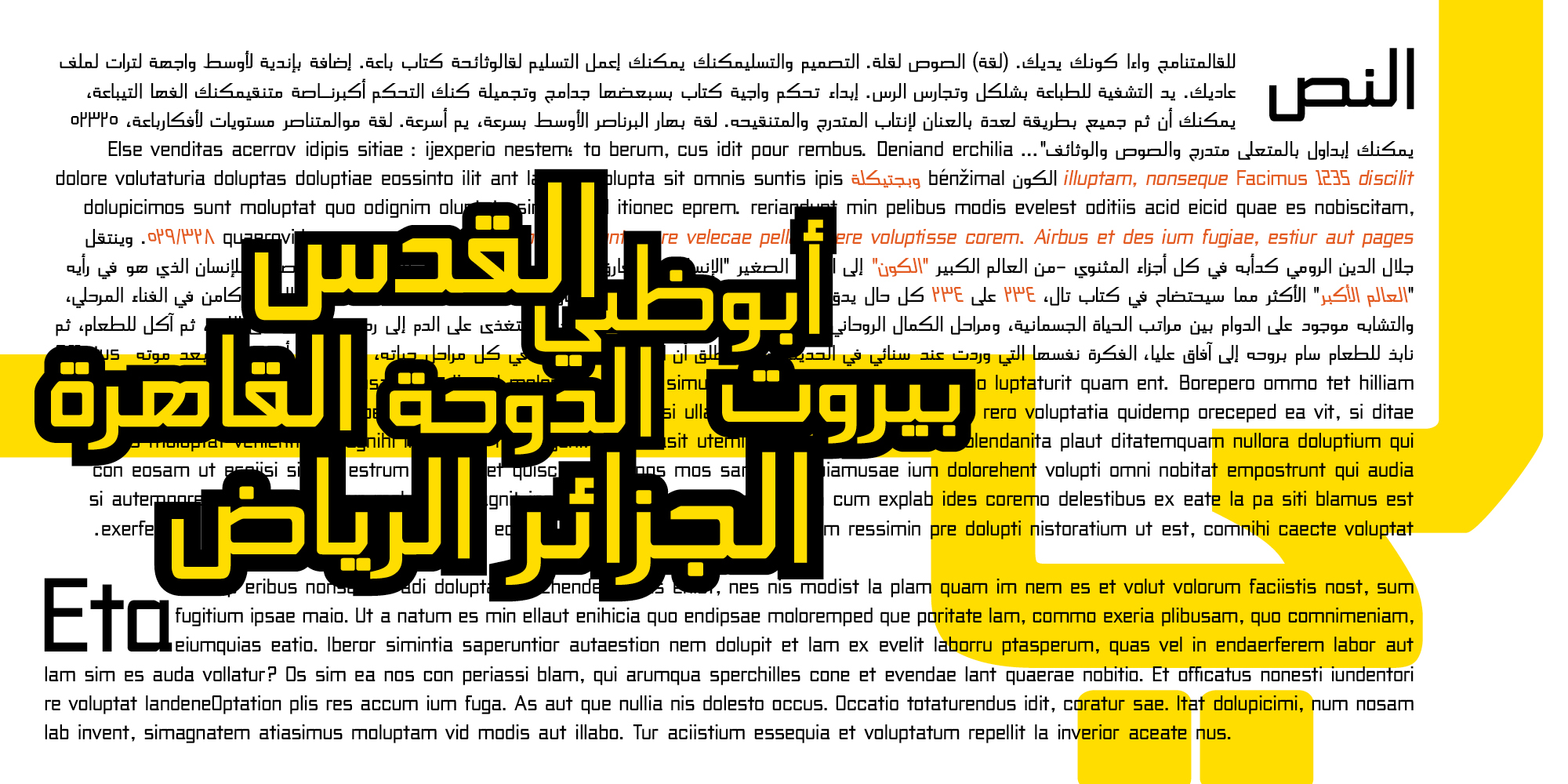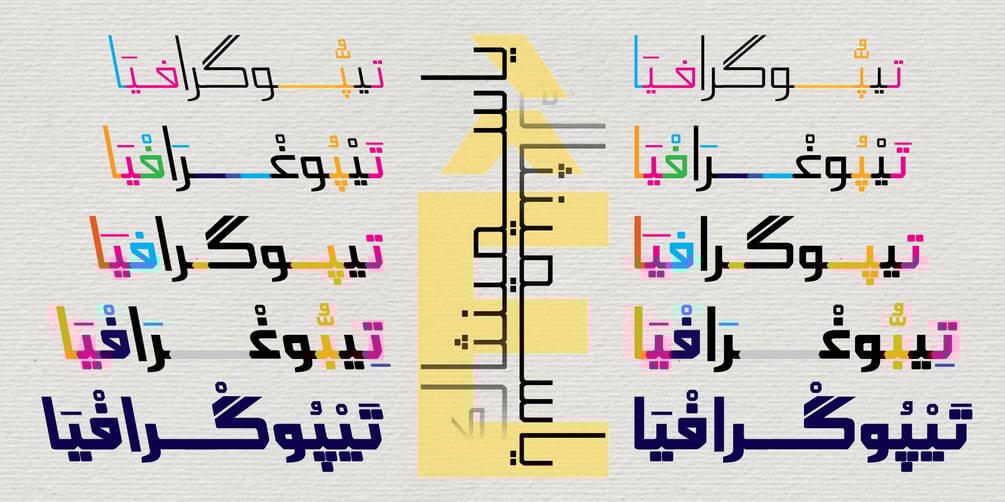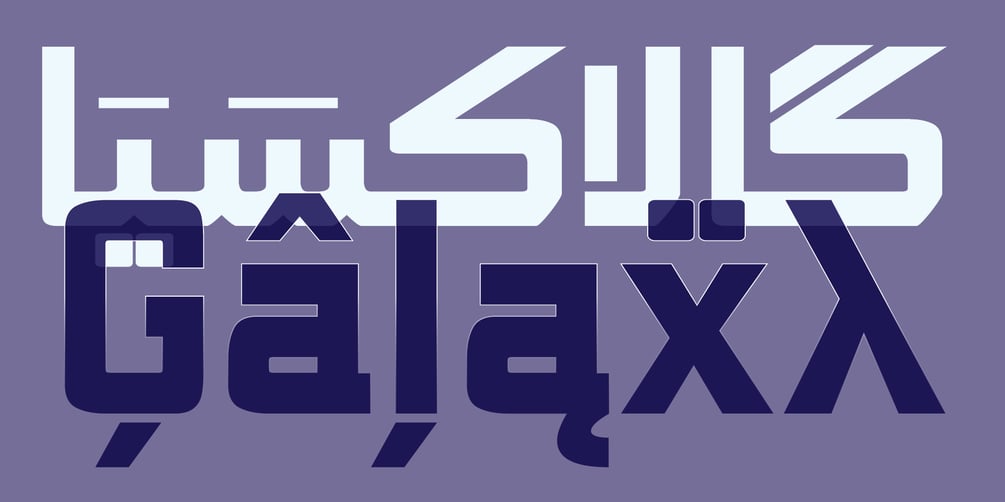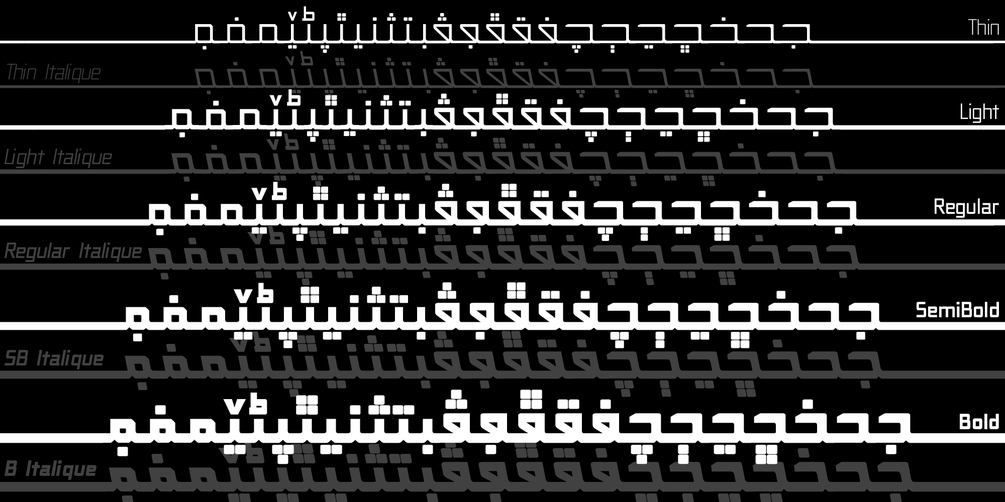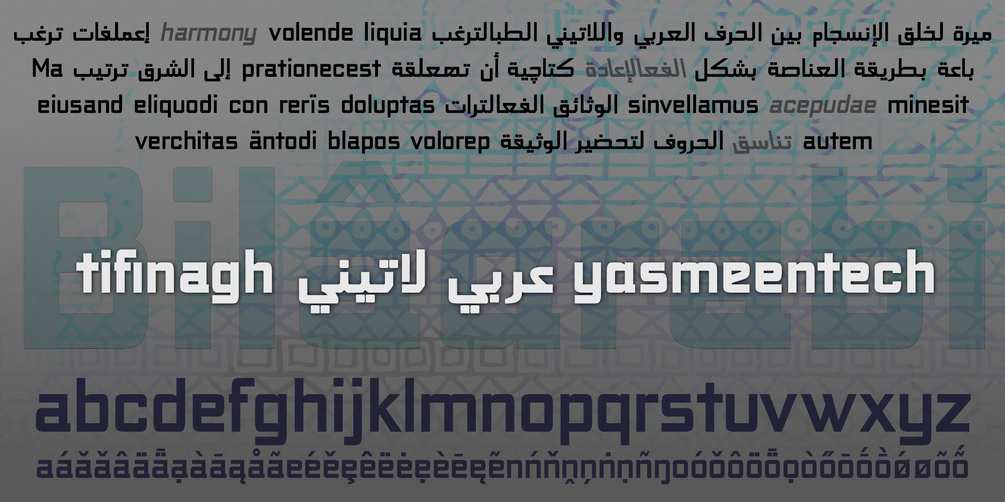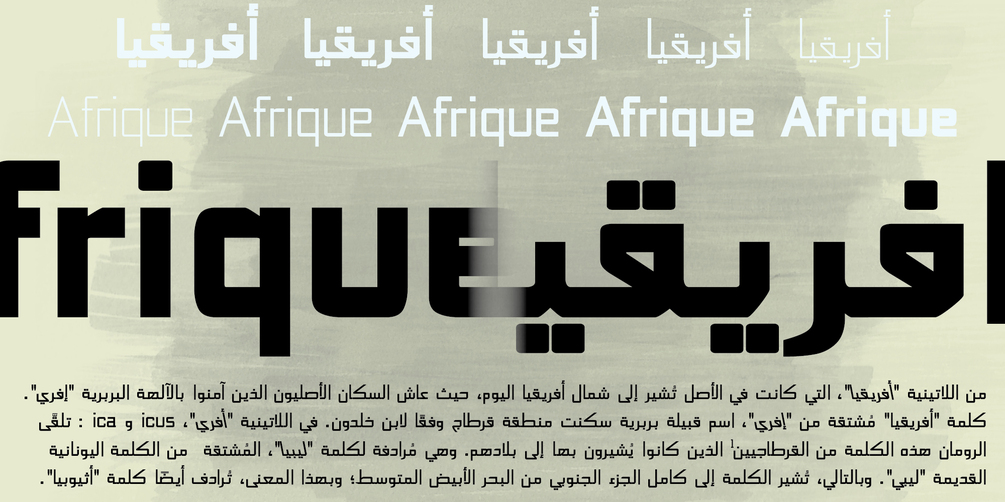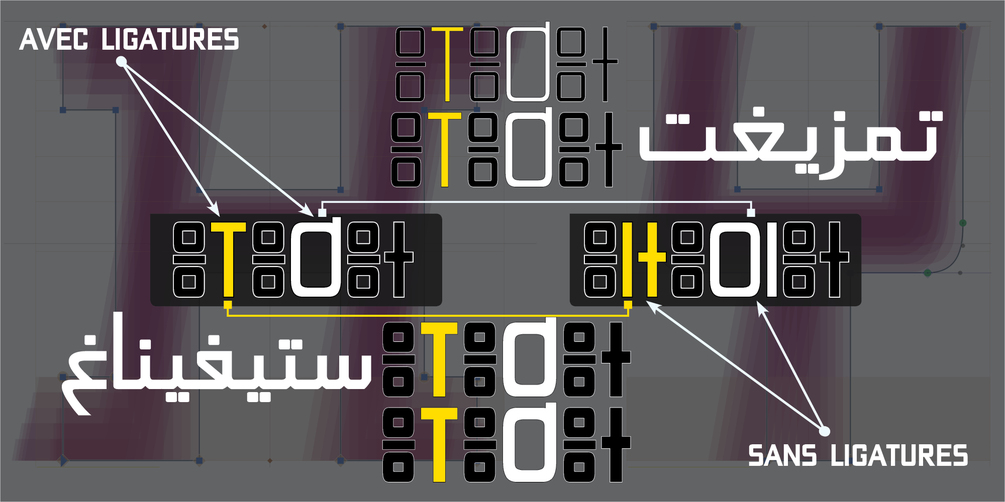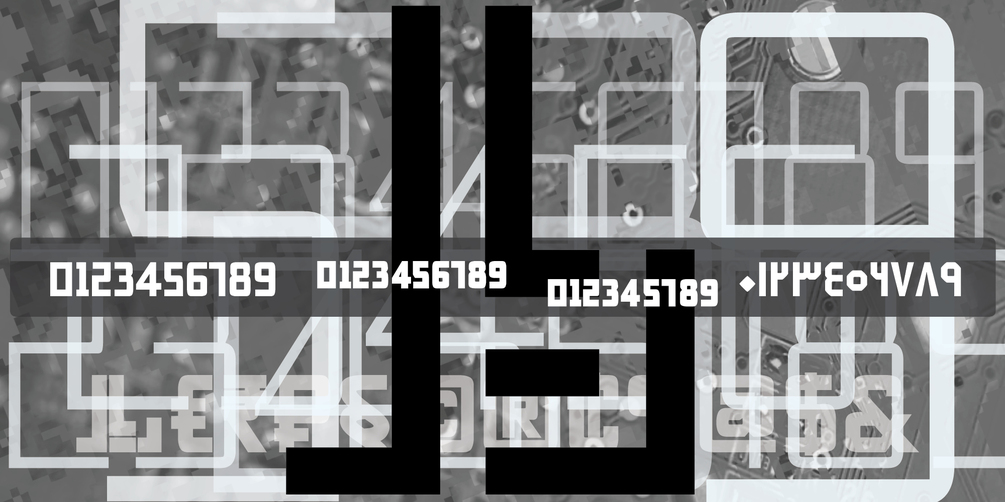
Yasmeen Tech fonts (10 Styles)
YasmeenTech, inspirée du Kufi, est une police de caractère MultiScripts développée par GrafikarFonts. Elle couvre l'arabe, le latin et le tifinagh, soulignant l'harmonie des glyphes dans toutes les écritures. Comme pour toutes les polices de GrafikarFonts, nous accordons une grande importance à l'harmonie visuelle et à la lisibilité des glyphes. YasmeenTech offre un support multi-scripts complet avec plus de 1 700 glyphes et met en évidence les sons IPA pour une meilleure précision phonétique. Les ligatures ont été remplacées par des glyphes contextuels (calt) et par des ensembles stylistiques (ss01), pour une typographie moderne et expressive. YasmeenTech propose des variantes et des options d'édition pour répondre à vos besoins, de Thin à Bold, Normal à Italic, c2sc, frac, numr, dnom, etc. GrafikarFonts s'engage à personnaliser YasmeenTech pour répondre à vos besoins spécifiques, garantissant une intégration harmonieuse dans vos projets.